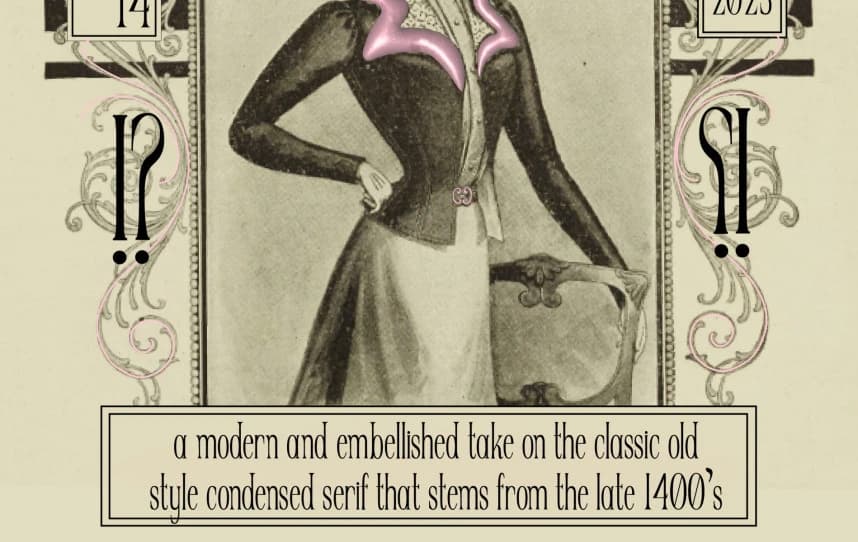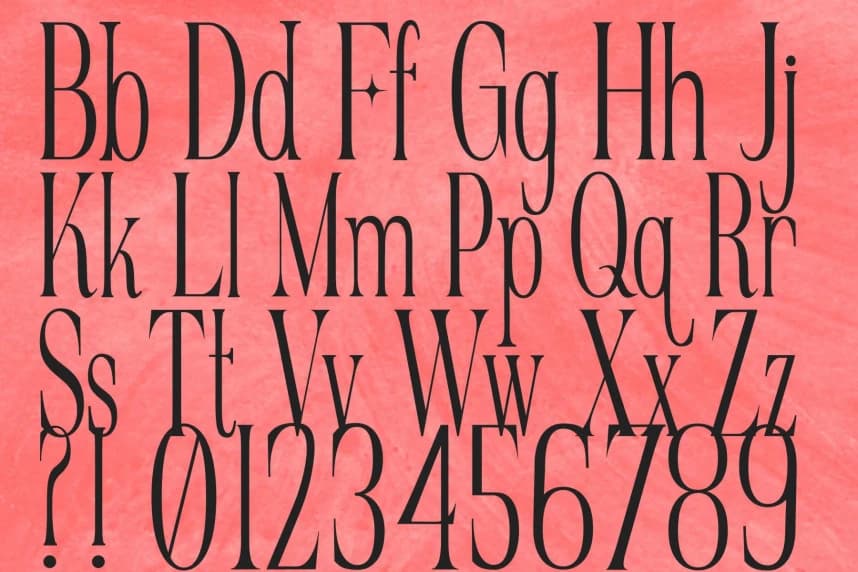
Bronze Copper Font, klasik eski tarz sıkıştırılmış serif yazı tipinin modern ve süslü bir yorumu. İncelikli vintage karakteri, zarif orantıları ve dekoratif ayrıntılarıyla bu yazı tipi, herhangi bir tasarıma zamansız ancak sofistike bir hava katar.
Bronze Copper Font, klasik eski stil dar serif yazı tipinin modern ve süslü bir yorumu. Özenli vintage karakteri, zarif oranları ve dekoratif ayrıntılarıyla bu yazı tipi, her tasarıma zamansız ama sofistike bir hava katıyor.